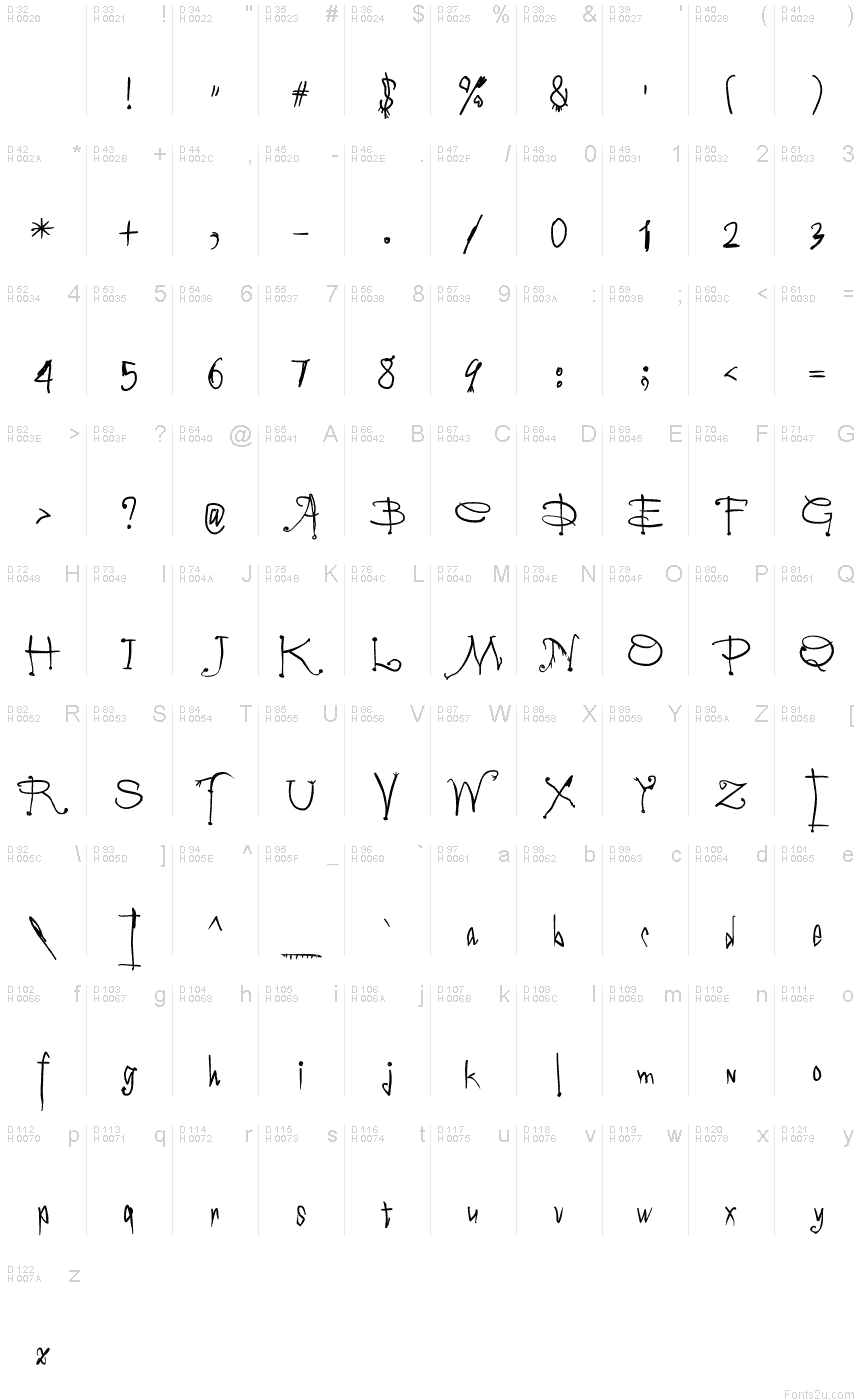
Vampyriqua di Manfred Klein è un font gotico scritto a mano, gratuito, dal carattere inquieto e notturno. Le lettere sembrano incise con un pennino affilato, mescolando tratti sottili, punte improvvise e un ritmo quasi perturbante, più vicino alle atmosfere horror vintage e ai romanzi pulp di vampiri che a una scrittura casuale.
Questo rende il font ideale per poster horror, volantini di Halloween, copertine di fanzine, artwork di band e titoli inquietanti. È perfetto anche per brevi progetti di branding, come etichette per bevande o incipit di capitoli, dove queste lettere irregolari e pungenti bastano a definire l'intero mood senza bisogno di altro.